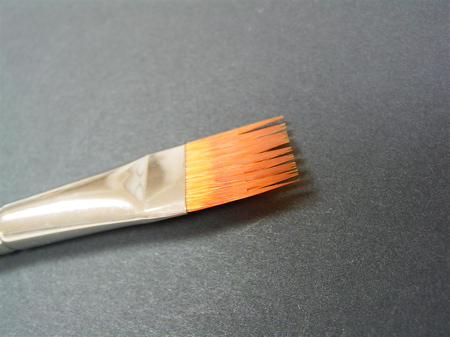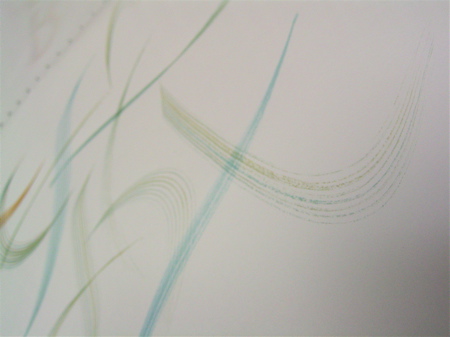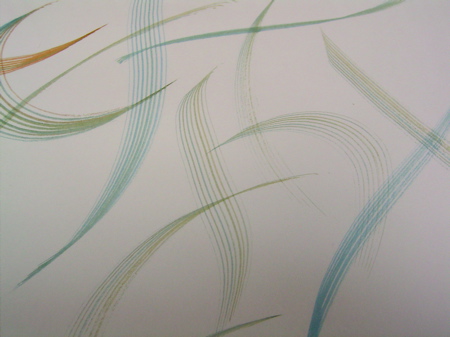
平筆すきまあり
先日ウエマツに行ったときに、見つけたのですよ。
平筆すきまありを。
日本画の道具の所にあったのですが、日本画でも平筆を使用するのでしょうか。 そもそも、日本画でも平筆を使うのですねぇ。そうなんだ〜。
一体どんな風に使うのか知りたいですが、私達はやっぱり文字とか線とか書くのです
。今までは均等な隙間を作るには、オートマチックペンしかありませんでしたが、やはりあれは固い線です。
でも見て!ホラ、こんなにやわらか〜〜な線が出ますですよ。
平筆で上手に文字を書けたらよいですよね。平筆ローマンはみんなの憧れ!
いつかちゃんと習いたいなぁ・・・。
平筆すきまあり、買うべしです!
こりゃすごい…
見た感じは普通の筆に見えるのに、こんな綺麗な線がかけるんですか〜
カリグラフィーじゃなくても普通の水彩画にも使えそうですね。
勉強になります
あっ!なんか昔買った覚えがある。たしかこの引き出しの奥に…あった!買ったはいいもののどないしよと買ったままの状態でしまってたんだ!たしかトールペイント売場で買ったような。早速使ってみまーす!
そうなのです。平筆はカリグラフィーにも使うのです。
2000年前のローマの碑文にも下書きで使用されてたと言われているくらい、古くから使われているそうですよ
そうでしたか、引き出しの中に長年潜んで出番を待っていたのですね。さぁさぁ使いましょう、使うのですよ〜!